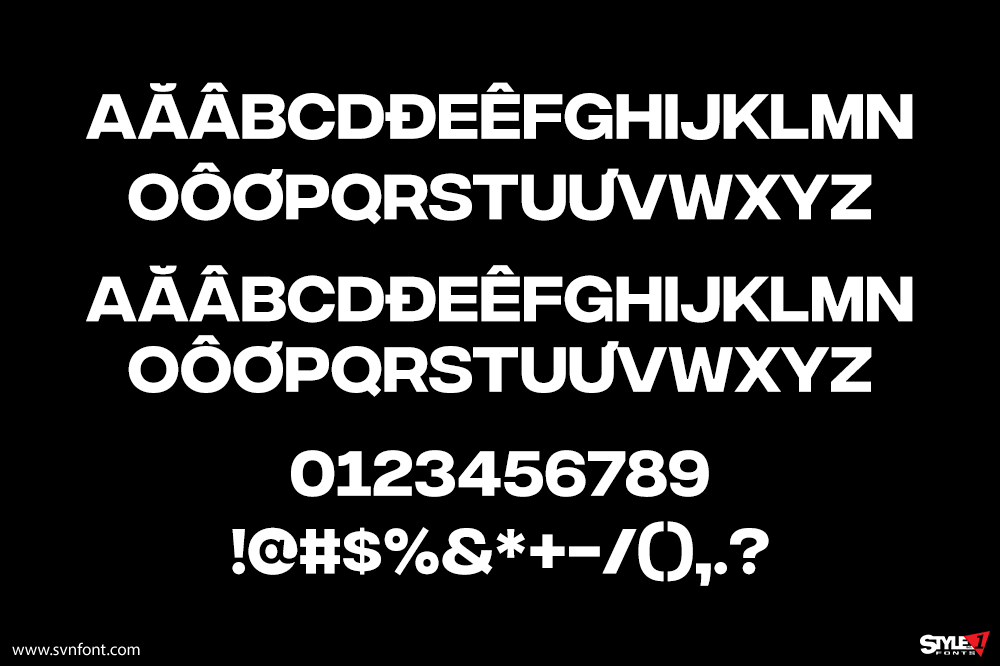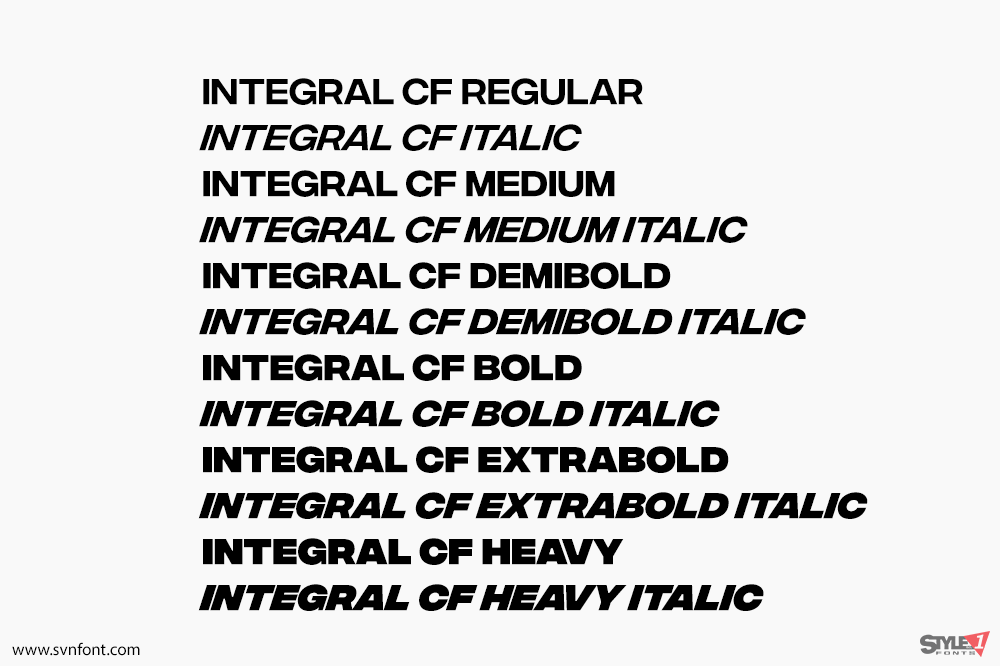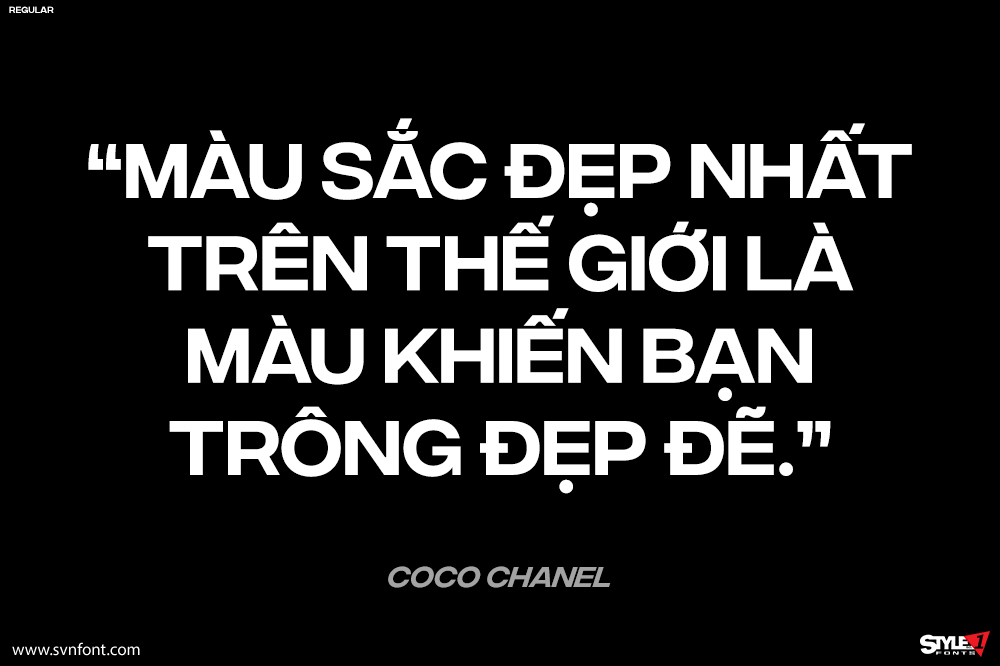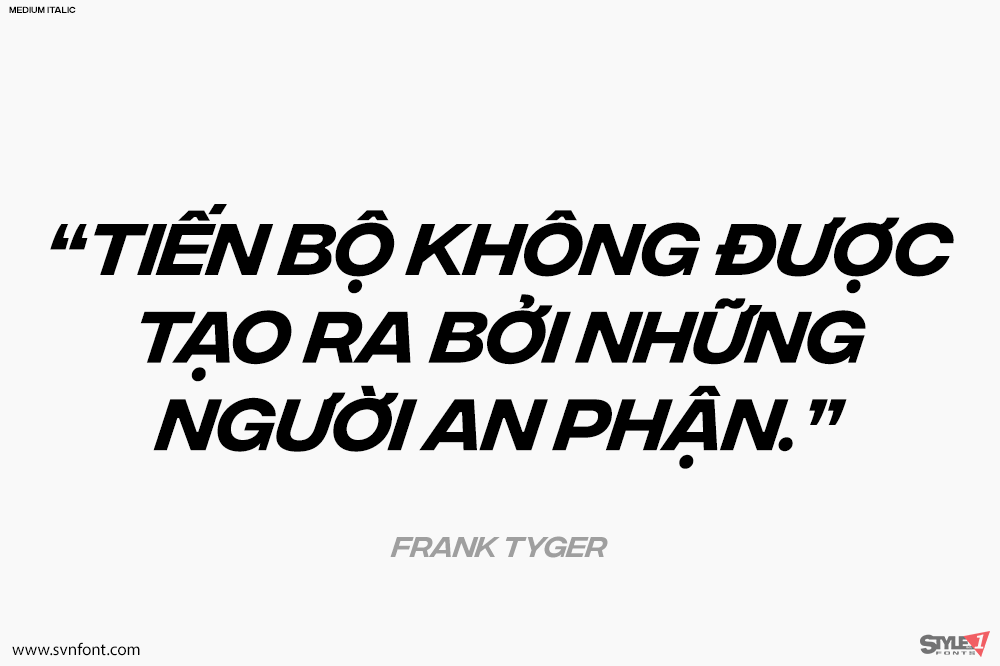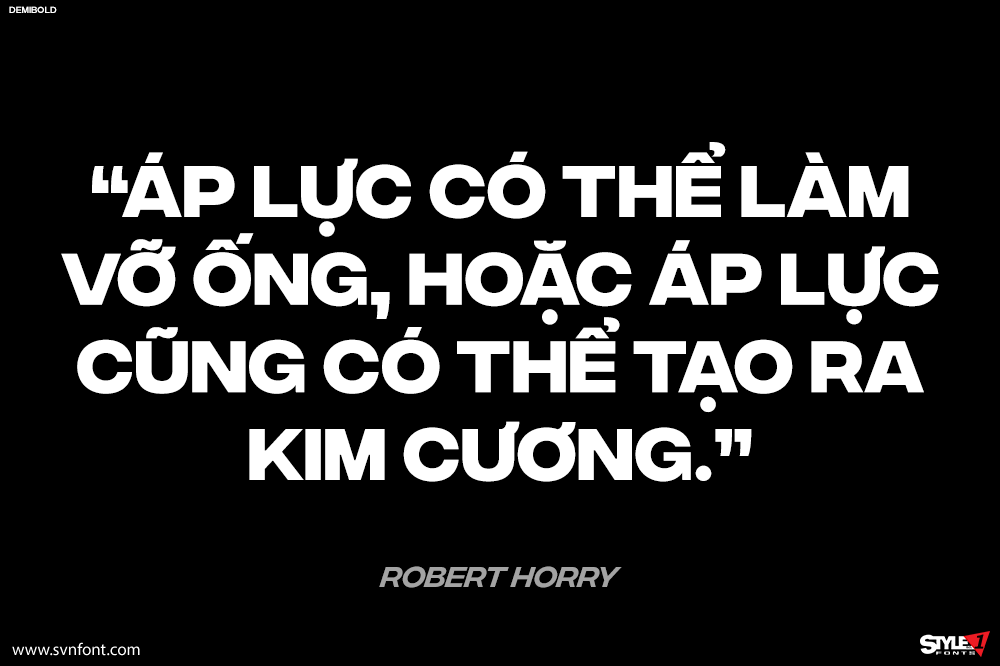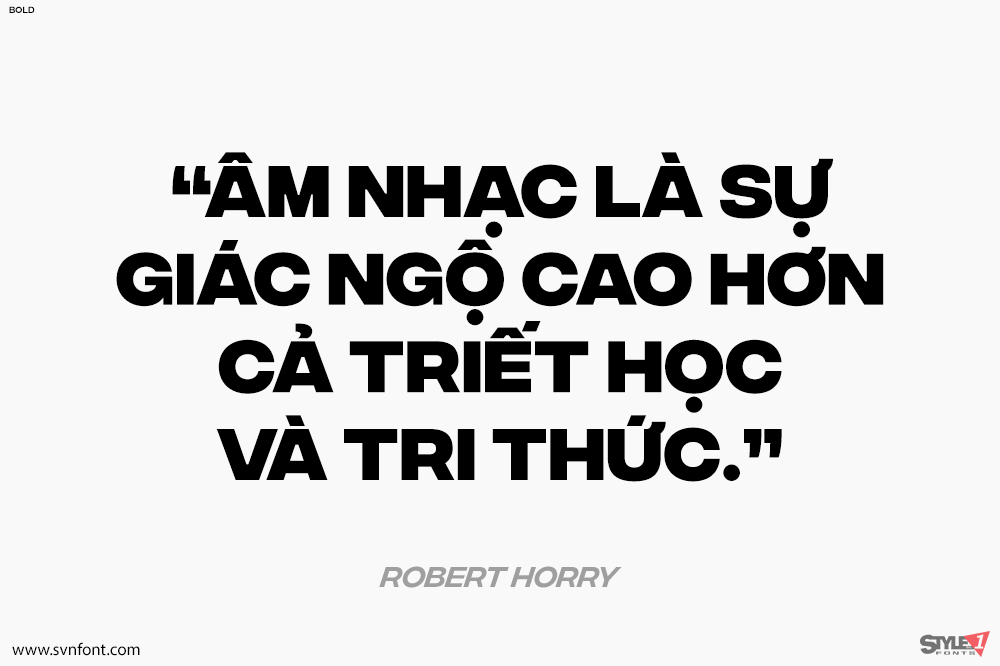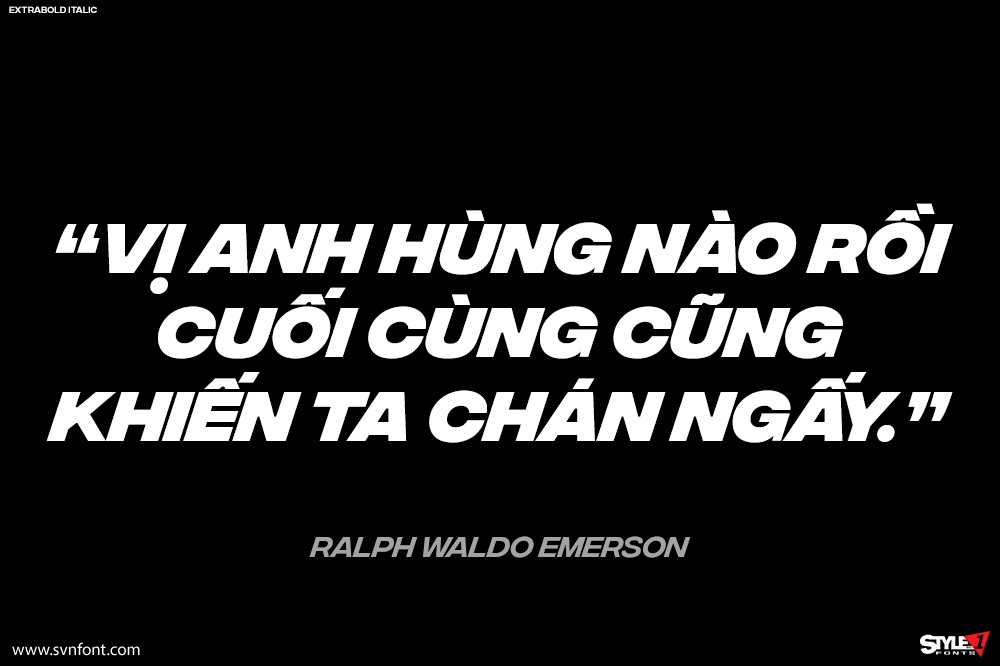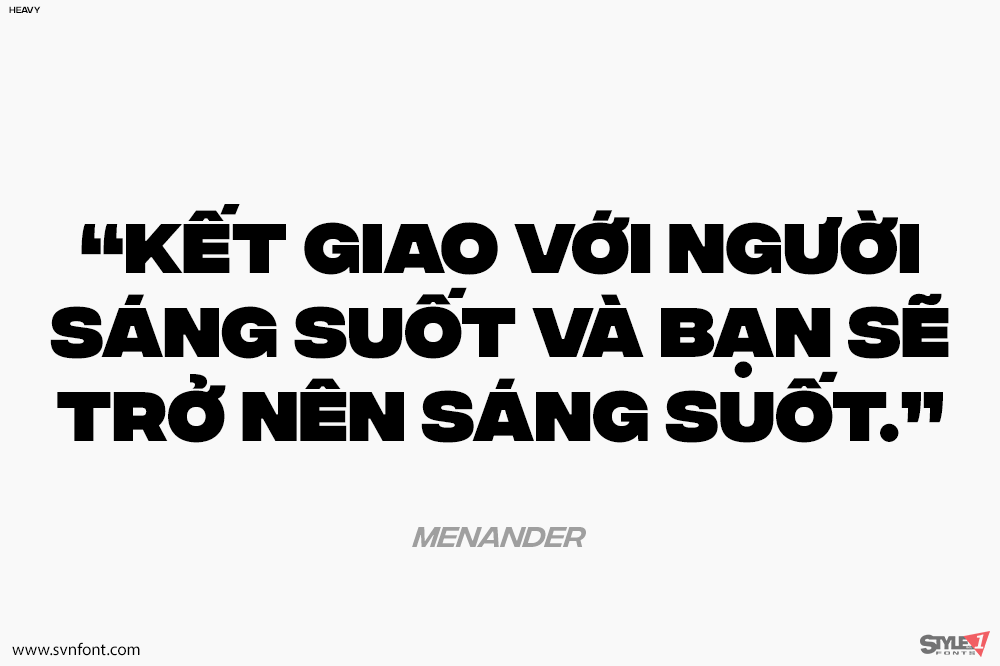
Integral CF được thiết kế để tạo ra tác động thị giác và cảm xúc tối đa. Sáu độ đậm của phông chữ này đặc biệt nổi trội trong các thiết kế poster, mạng xã hội, tiêu đề chính, tiêu đề phụ, ấn phẩm khổ lớn – và bất cứ nơi nào bạn muốn thu hút sự chú ý. Ẩn sau những đường thẳng và vẻ ngoài tự tin, chuyên nghiệp là một chút nét quyến rũ và cá tính nổi loạn. Integral mang đến cho lời nói của bạn một “giọng” mạnh mẽ, đồng thời rất thú vị khi sử dụng.
Nhà thiết kế: Connary Fagen
Nhà phát hành: Connary Fagen